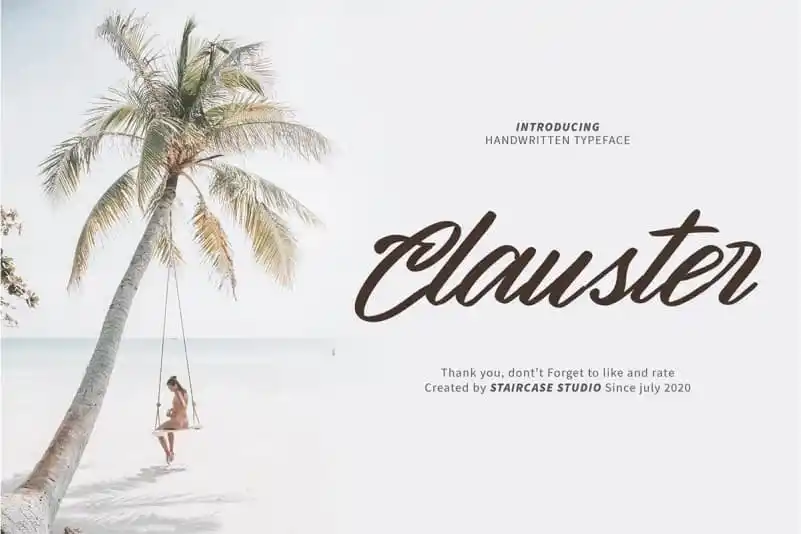
A Clauster Brush Font é uma escolha irresistível para projetistas de design que procuram adicionar um toque artesanal às suas criações digitais. Esta elegante e única fonte foi criada pelo talentoso estilista de fontes StairCase Studio, resultando em letras e números perfeitos tanto para trabalhos corporativos quanto para logotipos, design de marca, arte digital, camisetas e materiais de moda, panfletos, publicações de mídia, sinalização e design gráfico. Com um charme único que não poderia ser encontrado em qualquer outra fonte, a Clauster Brush é uma escolha perfeita para dar um toque especial às suas criações digitais ou impressas, tornando-a a escolha ideal para designers buscam personalidade em seus projetos.